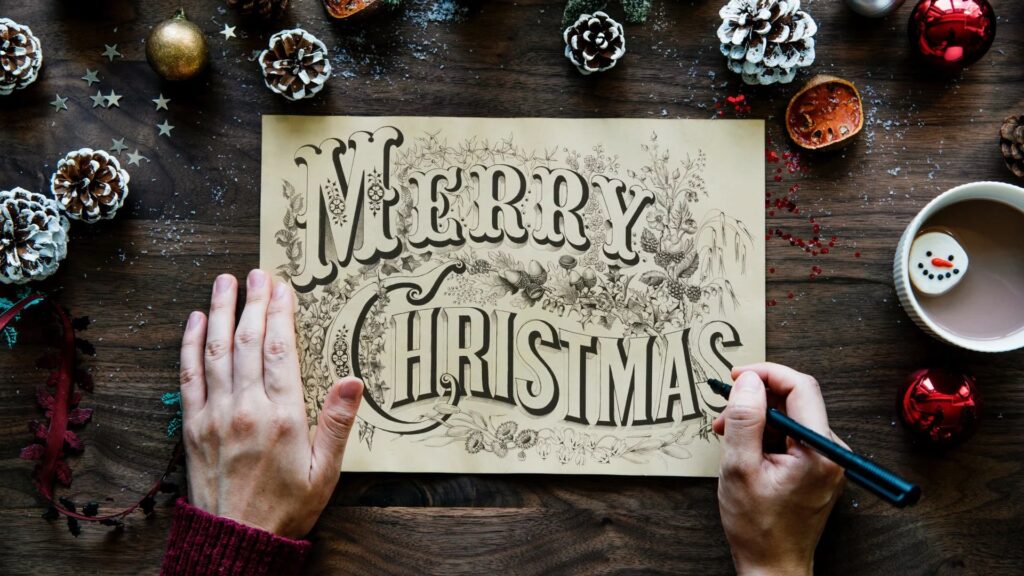
Når den hyggelige juletid nærmer sig, fyldes vores verden med lys, farver og en helt særlig stemning. Som entusiaster af visuelt design – hvad enten det er fotografi, grafisk design eller blot at lave smukke julehilsner – ved vi, hvor vigtigt hvert element er for at fange denne stemning. Et ofte overset, men utroligt effektivt værktøj til at formidle juleglæde og festlighed er skrifttypen. Valget af den rette font kan transformere et simpelt design eller et billede med tekst til noget, der emmer af jul.
Hvorfor er Skrifttypen Vigtig til Jul?
Forestil dig et julekort, en festlig invitation, et skilt til et julemarked eller måske endda en vandmærket julefotografi – skrifttypen er ofte det første, der møder øjet efter selve billedet eller layoutet. Den sætter tonen og kan øjeblikkeligt signalere 'jul'. En velvalgt julefont kan:
- Fremkalde følelser: Nogle skrifttyper føles varme og hyggelige, andre elegante og sofistikerede, og atter andre sjove og legesyge – præcis som julen kan være på mange måder.
- Tilføje festlighed: Dekorative elementer som snefnug, hjerter, eller svungne linjer indbygget i bogstaverne skriger 'jul'.
- Skille sig ud: I en tid hvor mange visuelle budskaber deles, kan en unik og passende julefont fange opmærksomheden.
- Styrke dit budskab: Om du annoncerer et julesalg, ønsker glædelig jul på et familiebillede eller designer en menu til julefrokosten, understøtter fonten budskabet.
Det handler ikke kun om at bruge rød og grøn. Typografi er et kraftfuldt designelement i sig selv, der kan bidrage markant til den samlede visuelle balance og stemning i dine juleprojekter, hvad enten de involverer fotografi eller ej.
Find den Perfekte Julefont: Hvad Skal du Overveje?
At finde den 'gode' julefont er subjektivt og afhænger helt af det ønskede udtryk. Skal det være klassisk og tidløst, moderne og stilfuldt, eller sjovt og finurligt? Her er nogle faktorer at overveje:
- Læselighed: Dette er altafgørende, især hvis fonten bruges til længere tekst eller vigtige informationer (som datoer på invitationer). Meget dekorative fonter er ofte bedst til overskrifter eller korte sætninger.
- Stil vs. Enkelhed: En meget dekorativ font kan 'stjæle billedet'. Hvis du bruger en sådan, bør resten af designet (billeder, farver) måske holdes mere afdæmpet for at undgå et rodet udtryk. Omvendt giver en mere enkel, klassisk font plads til mere eksperimentering med billeder og grafik.
- Projektets Kontext: Hvilken type projekt er det? En elegant script font passer måske bedst til et formelt julekort, mens en sjov, legesyg font er perfekt til en invitation til et børnejulearrangement eller en festlig social media post.
- Kompatibilitet med Billeder: Hvis fonten skal bruges ovenpå et fotografi, skal den have tilstrækkelig kontrast til baggrunden for at være læselig. Overvej fontens tykkelse og farve i forhold til billedet.
Julen er traditionernes tid, og mange fonter emulerer svundne tiders stil. Andre er helt nye og fokuserer på den festlige, sjove side af højtiden. Dit skrifttypevalg afhænger helt af, hvad du ønsker at opnå med dit design.
Populære Julefonter til Inspiration
Der findes et utal af julefonter, både gratis og betalte, der hver især bringer deres egen unikke juleånd. Her er et udpluk af stilarter og eksempler, der kan inspirere dine designprojekter:
Elegante og Klassiske Julefonter:
Disse fonter udstråler raffinement og tidløs skønhed. De er ofte baseret på script- eller serif-stilarter med fine detaljer.
- Chopin Script: En smuk script font med tynde streger og diskrete accenter. Den er meget elegant og alsidig til mange julemotiver, især hvor et sofistikeret udtryk ønskes, f.eks. på et julekort med et stemningsfuldt portræt.
- Saint Nicholas: En traditionel serif font, der minder om gamle historiebøger, men med en klar juleånd, f.eks. små diamantformer i stregerne. Den er klassisk uden at være prangende.
- Santa’s Sleigh: En elegant serif font med et strejf af art nouveau. Dens svungne former giver bevægelse, og de tynde streger gør den yndefuld. Fantastisk til et stilfuldt design eller en overskrift på et fotoalbum.
- Great Vibes: En stilfuld og elegant script font med dekorative svirp, velegnet til sofistikerede julebudskaber.
Legesyge og Dekorative Julefonter:
Disse fonter inkorporerer ofte julemotiver direkte i bogstaverne eller har en karikaturagtig stil. De er perfekte til sjove, uformelle projekter.
- Candy Cane: Denne sans-serif font efterligner udseendet af en sukkerstok med striber indbygget i bogstaverne. Den er dynamisk, læselig og utroligt julet. God til moderne designs eller overskrifter på sociale medier.
- PW Christmas font: En dristig sans-serif script font med små tegninger og bånd omkring bogstaverne, der får hvert tegn til at ligne en lille gaveæske. Stråler af glæde og er meget unik.
- Christmas Tree Lights: En finurlig font med julelys, der snor sig omkring bogstaverne. Perfekt til at gøre et design levende og gøre fonten til hovedattraktionen.